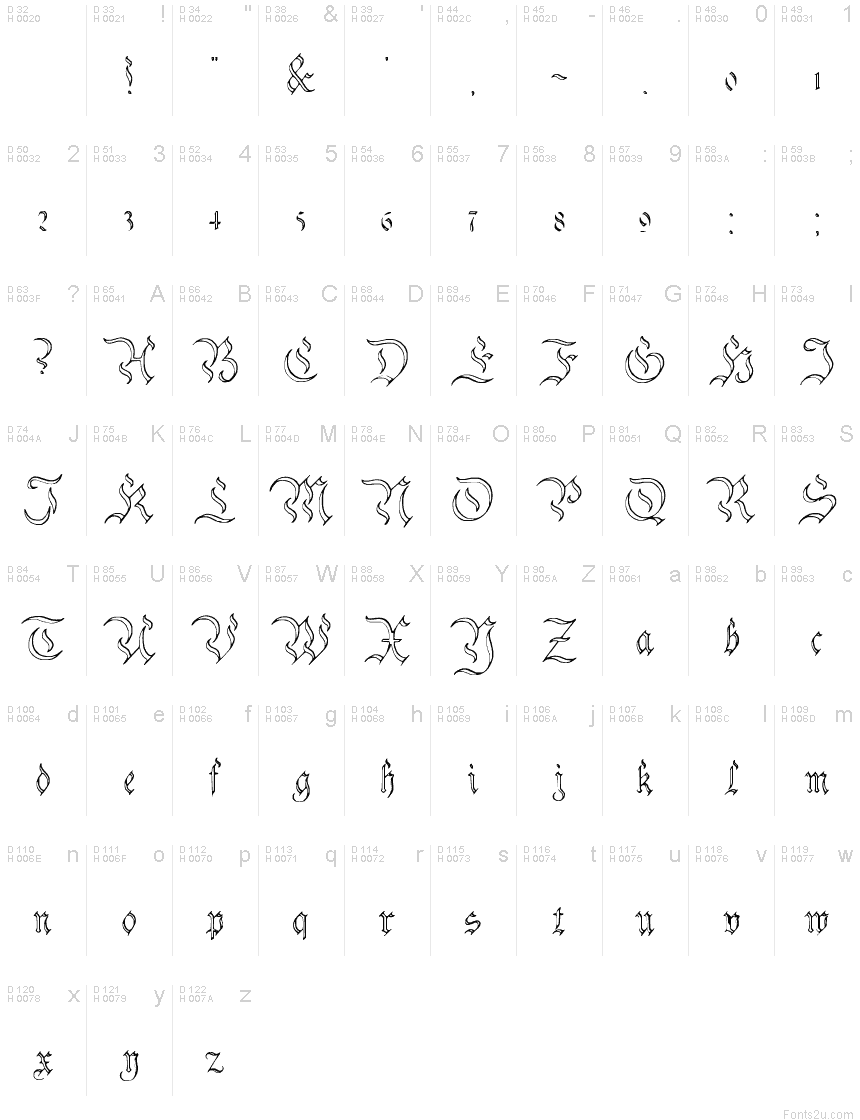
Charterwell No3 od PJL to darmowy gotycki, średniowieczny krój pisma. Jego ostre kreski, haczykowate krzywizny i wąskie, przypominające ślady pióra formy wyglądają, jakby zostały wyjęte ze średniowiecznego rękopisu, a nie narysowane na ekranie. Litery tętnią nieregularną, surową energią, nadając nagłówkom ceremonialny ciężar zamiast sztucznej, wygładzonej doskonałości.
Dzięki Charterwell No3 Twój tekst natychmiast przywodzi na myśl starożytne zwoje, światy fantasy czy plakaty w stylu dark metal. Ten darmowy font świetnie sprawdzi się na okładkach książek, w kampaniach RPG, logotypach zespołów, plakatach imprezowych, szkicach tatuaży czy nastrojowych projektach brandingowych. Stosuj go w dużym rozmiarze, aby zachować wyrazistość detali, i zestawiaj z prostym fontem bezszeryfowym w tekście uzupełniającym – dzięki temu Twoje projekty pozostaną czytelne, a Charterwell No3 przyciągnie całą uwagę.